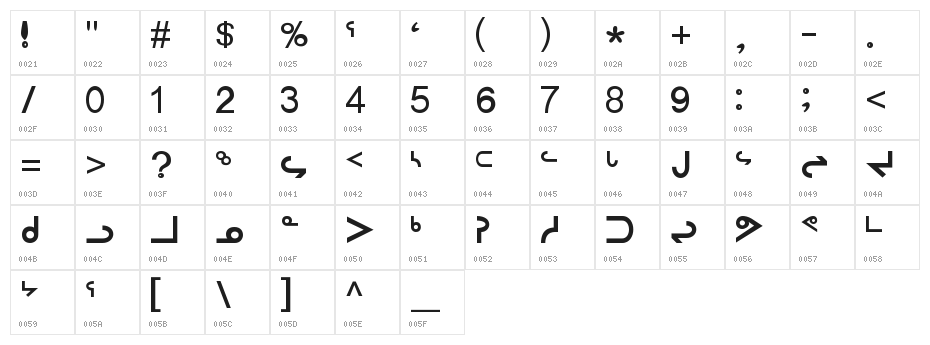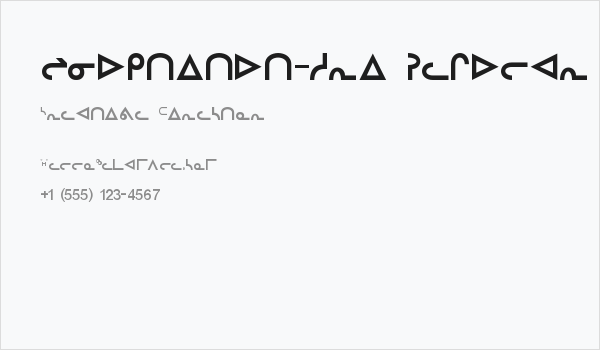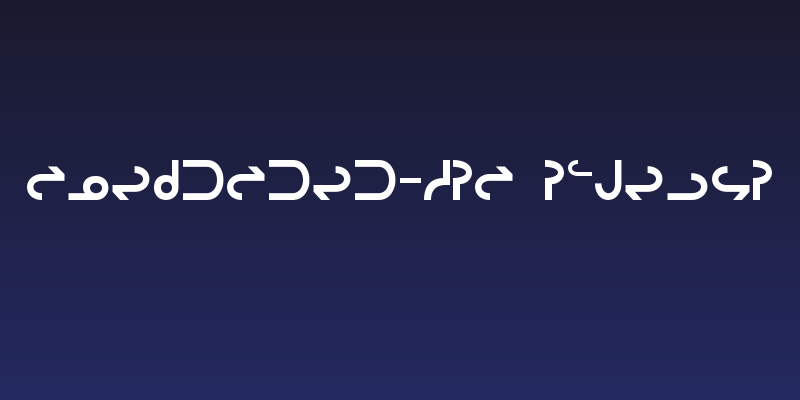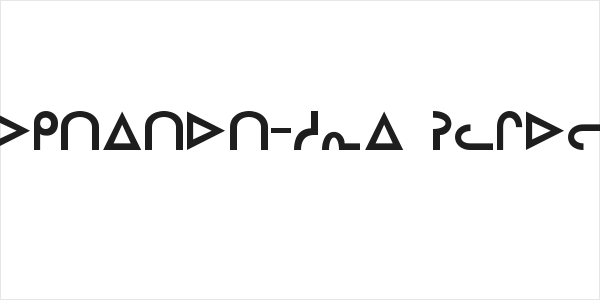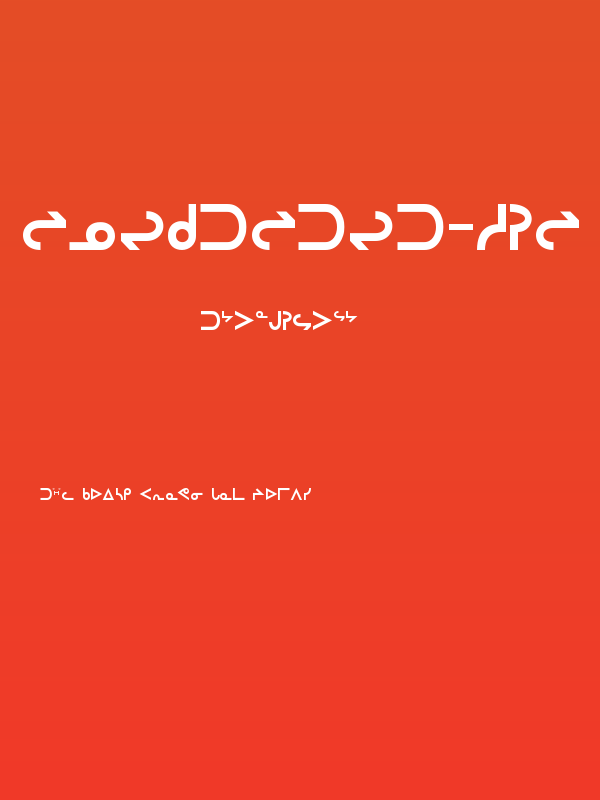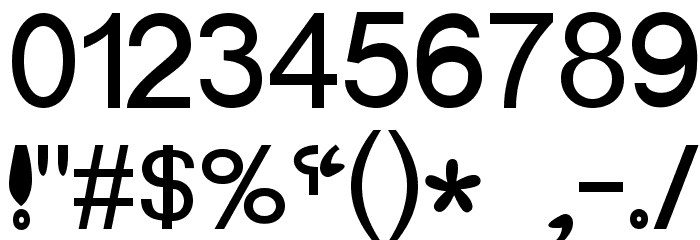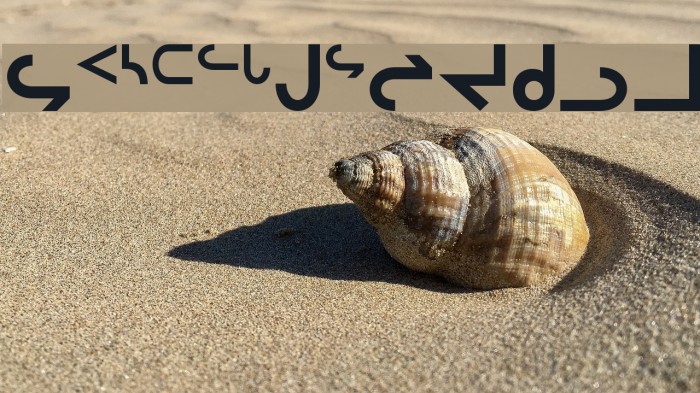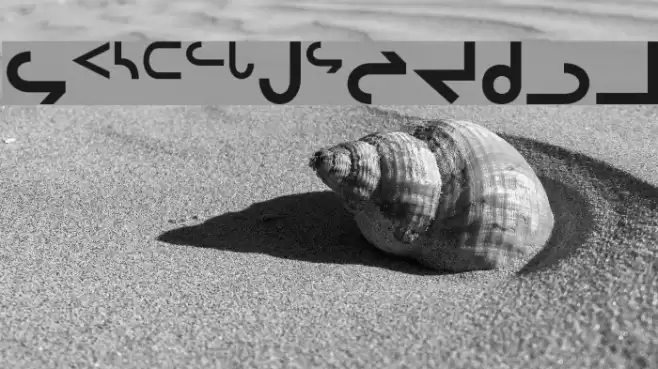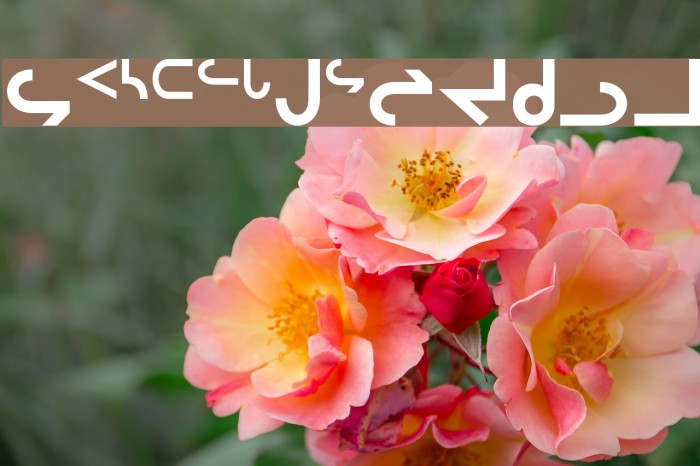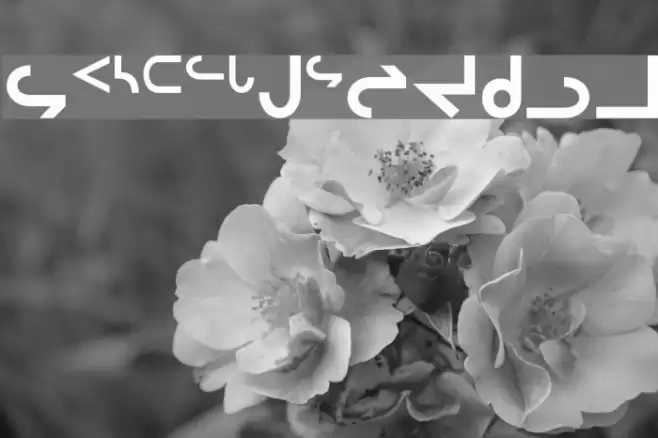
Inuktitut-Sri Regular Font
| Cas d'utilisation | Headlines, Logos, Signage |
| Projets proposés | Ideal for cultural projects, educational materials, signage, and branding that require a modern yet traditional touch. |